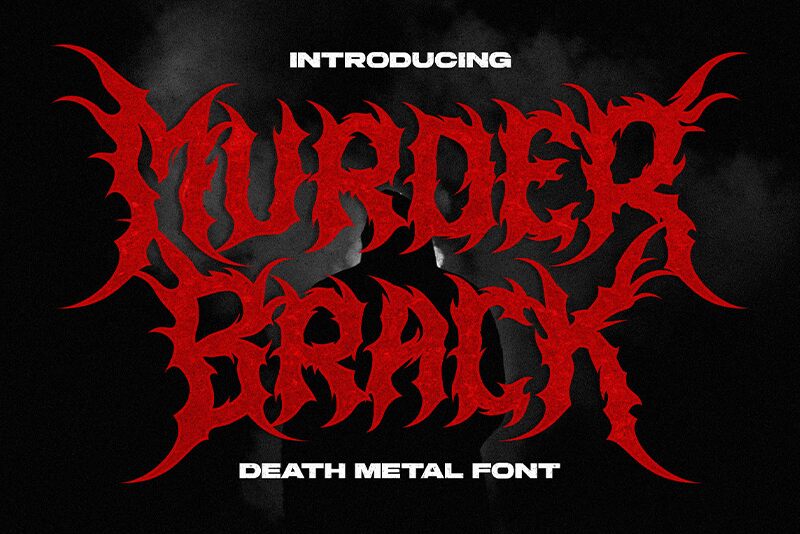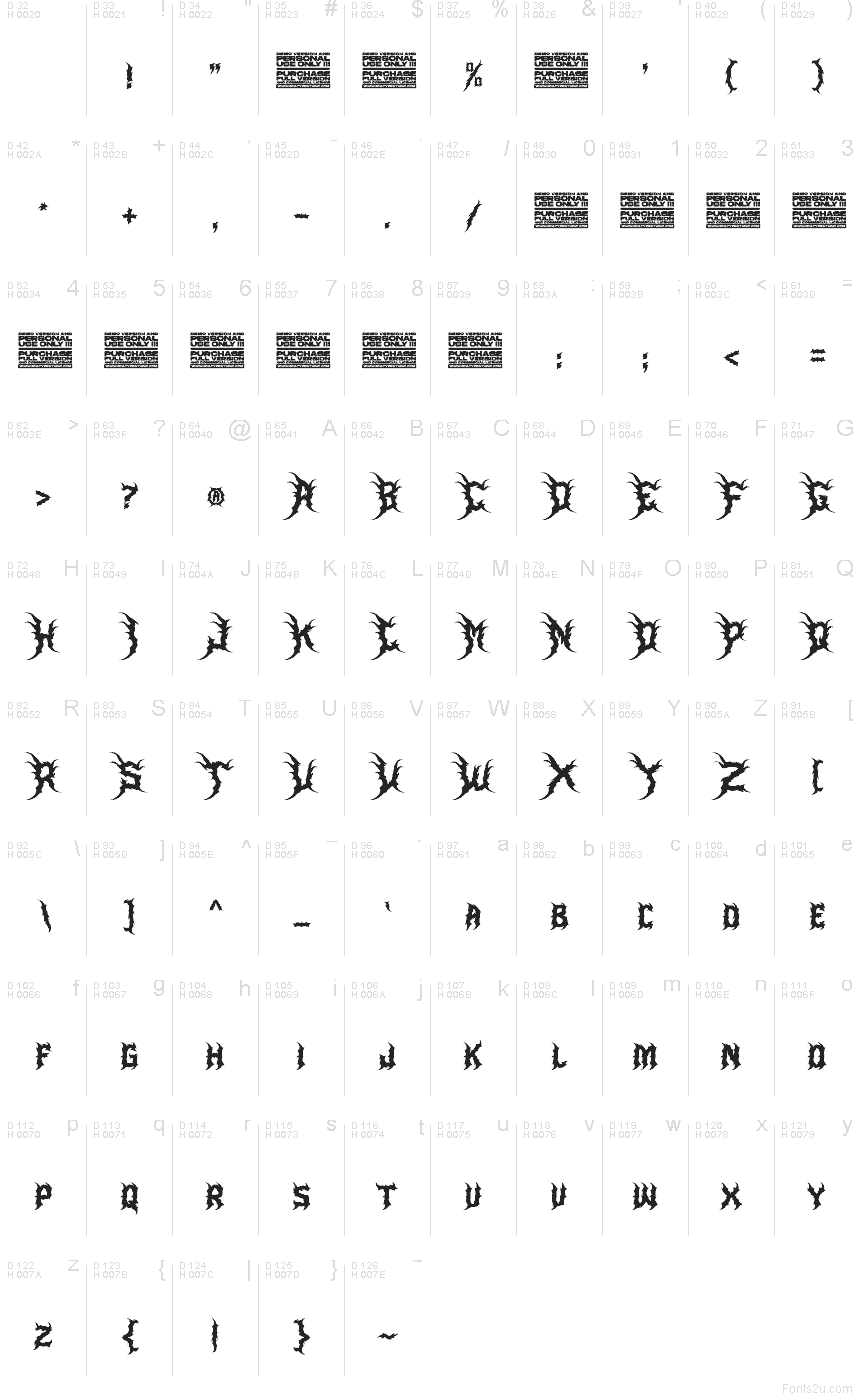
Murder Brack
Murder Brack da Multype Studio é uma fonte gótica gratuita com traços afiados como espinhos e glifos quebrados e pontiagudos, conferindo ao conjunto um aspecto rústico, como se tivesse sido esculpido. As formas são compactas e angulares, com bordas externas pontiagudas e espaços internos estreitos que tornam o letreiramento agressivo e ornamental ao mesmo tempo.
Murder Brack é uma fonte gratuita perfeita para logotipos de bandas de metal, pôsteres de terror, títulos de jogos, artes de tatuagem, capas de álbuns e flyers de eventos que exigem uma voz gótica sombria. Seu ritmo irregular e ornamentação pesada tornam-na especialmente útil quando o texto precisa carregar o clima por si só, ou servir como um destaque dramático em cartazes, emblemas ou capas.